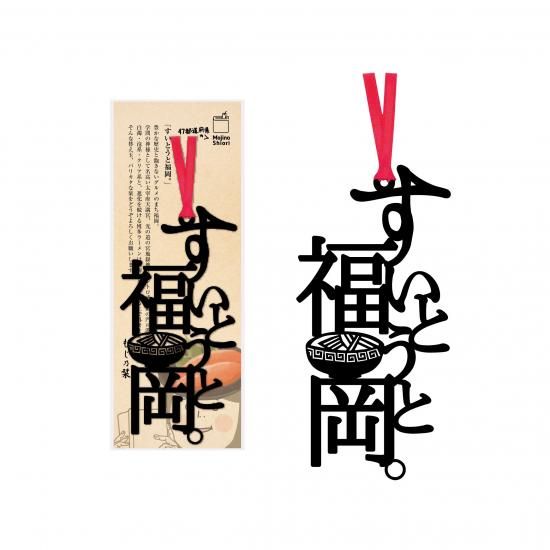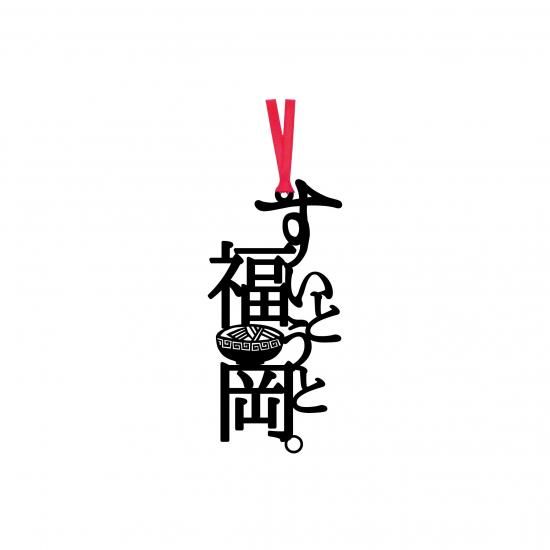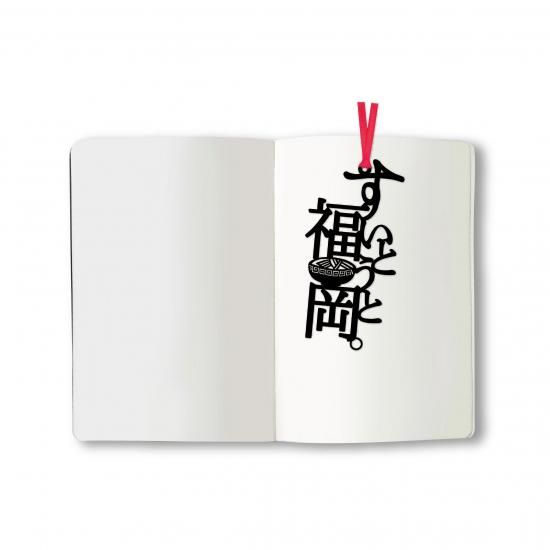
文字の47都道府県のしおり「すいとうと福岡。」
豊かな歴史と飽きないグルメのまち福岡。
学問の神様として名高い太宰府天満宮、光の道の宮地嶽神社、レトロ感満載の門司港など魅力は満載。
白濁・泡系・クリア系と、進化を続ける博多ラーメンは福岡グルメを語る上で外せません。
そんな替え玉、バリカタな栞をどうぞよろしくお願いします。
木材パルプや綿を原料とした環境素材を採用し、耐久性・耐水性に優れたファイバーの特徴を活かすことで、言葉がフォントごと切り取られたような巧緻で美しい『文字のしおり』のデザインが実現しています。